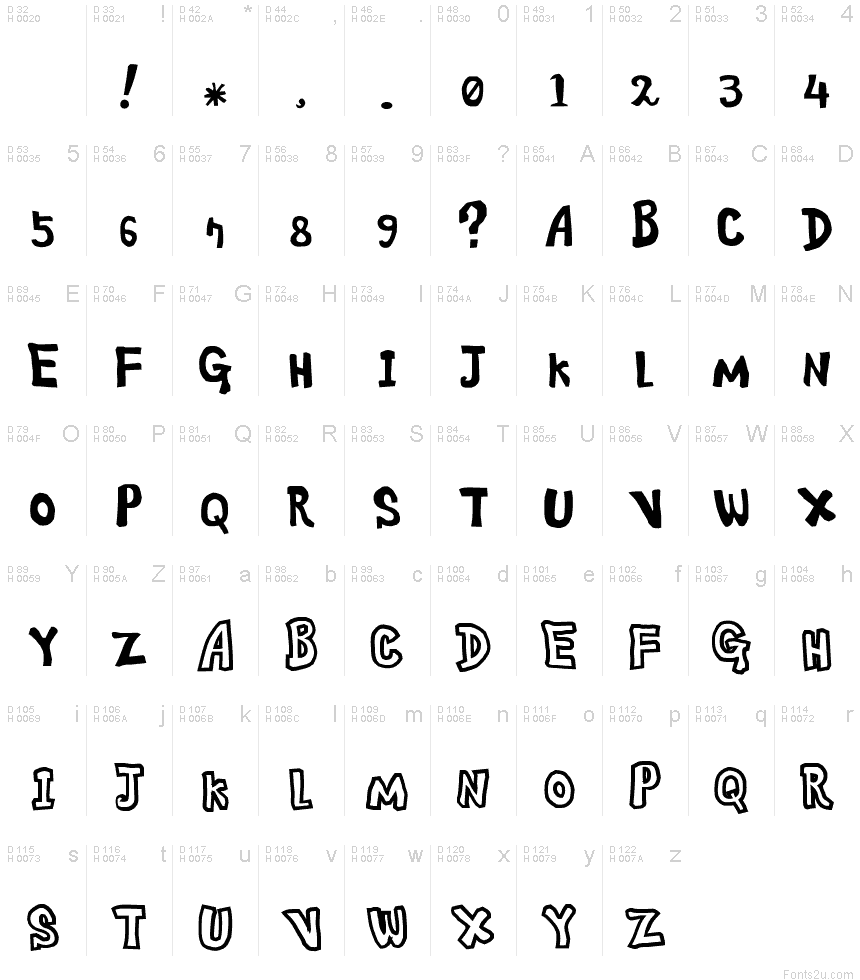
ananda od Tamon Yahagi je bezplatné komiksové display písmo s výraznými obrysy, hravým rytmem a ručně kresleným dojmem, který působí, jako by bylo právě načrtnuto do skicáku. Každé písmeno se naklání a protahuje tak akorát, aby působilo energicky, ale přitom přehledně. Dodá vašim nadpisům radostný a hlasitý tón namísto strohých titulků. Díky nepravidelným tahům a otevřeným vnitřkům písmen vypadá skvěle zejména ve větších velikostech.
S ananda dodáte okamžitý charakter komiksovým obálkám, fanzinům, názvům dětských knížek, hravým plakátům, samolepkám, letákům na akce i originálnímu brandingu. Tento font zdarma funguje skvěle všude tam, kde potřebujete zábavu, přátelskost a trochu toho „řízeného chaosu“, který zůstává na první pohled čitelný. Zkuste ananda zkombinovat s čistým geometrickým bezpatkovým písmem pro hlavní text a nechte tento výrazný komiksový font, aby se postaral o ty velké, hlasité nadpisy.